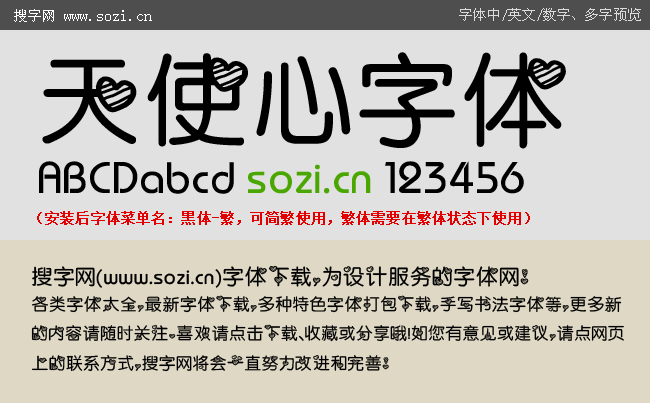
天使心字體
搜字網(wǎng)給大家提供一款天使心字體手機(jī)中文字體下載。這款手機(jī)字體是以圓體字體為原形,筆畫間嵌入了可愛的卡通心形圖案。在具備粗圓字體清晰醒目風(fēng)格的同時(shí),卡通味也特別濃,是一款非?蓯鄣目ㄍㄗ煮w,特別適合喜歡手機(jī)字體個(gè)性一些的朋友在手機(jī)上安裝使用。